Combinación Eficaz de Tipografías en Diseño Web
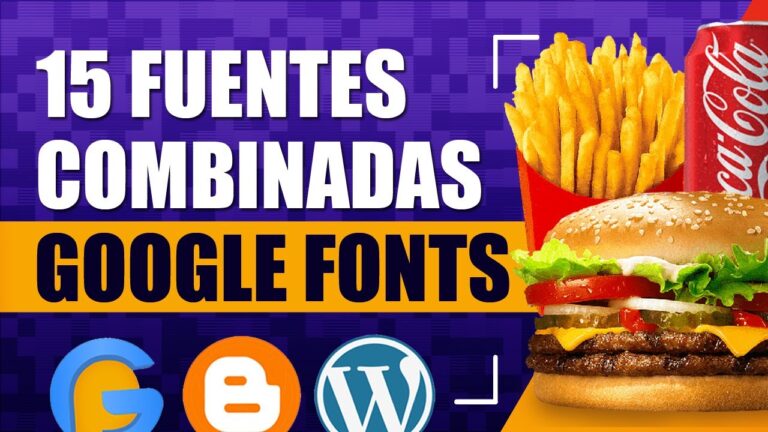
La combinación de tipografías en el diseño web es un arte que puede transformar la estética y la funcionalidad de una página. Elegir las fuentes adecuadas no solo mejora la legibilidad, sino que también refuerza la identidad de marca y crea una experiencia visual atractiva para los usuarios. En un mundo digital donde la primera impresión cuenta, dominar esta técnica se vuelve esencial para cualquier diseñador que busque destacar en un mar de contenido. Exploramos las mejores prácticas y estrategias para lograr una armonía tipográfica que cautive y comunique eficazmente.
¿Cuántas tipografías se sugiere usar en un diseño web?
Al diseñar una página web, se recomienda utilizar entre dos y tres tipografías para mantener una estética limpia y coherente. Una combinación rendidora puede ser la fusión de tipografías sans serif y serif, que aporta un contraste atractivo y mejora la legibilidad. Este enfoque no solo evita que el diseño se sienta abrumador, sino que también realza la experiencia del usuario, facilitando la navegación y la comprensión del contenido.
¿Cuántas fuentes son apropiadas para utilizar en un sitio web?
Al diseñar un sitio web, la elección de tipografías es fundamental para lograr una comunicación rendidora y estética. Aunque no existe una regla estricta sobre cuántas tipografías se deben emplear, lo ideal es limitarse a un máximo de tres. Esta restricción no solo ayuda a mantener una apariencia coherente, sino que también facilita la lectura y la navegación del usuario.
Optar por una tipografía versátil puede ser una excelente estrategia. Al encontrar una fuente que se adapte bien a la identidad del sitio, es posible utilizar diferentes pesos, como regular, medium y bold, para resaltar información importante sin necesidad de introducir nuevas tipografías. De este modo, se logra un equilibrio visual que mantiene la atención del visitante y refuerza la jerarquía del contenido.
Además, al limitar el número de tipografías, se mejora la carga del sitio y se optimiza la experiencia del usuario. Un diseño limpio y ordenado no solo es más atractivo, sino que también ayuda a transmitir el mensaje de manera clara y directa. En resumen, la clave está en la selección cuidadosa de tipografías que se complementen entre sí, creando una armonía que beneficie tanto la estética como la funcionalidad del sitio web.
¿Cómo puedo combinar fuentes?
Combinar fuentes de manera rendidora es un arte que puede realzar visiblemente cualquier diseño. Para lograr una armonía visual, es clave elegir tipografías que se complementen entre sí. Una buena práctica es seleccionar una fuente para los encabezados que sea audaz y llamativa, y una más sencilla y legible para el cuerpo del texto. Esto no solo crea un atractivo visual, sino que también mejora la legibilidad y la jerarquía de la información.
Además, es recomendable limitar la combinación a dos o tres tipos de fuentes para evitar una apariencia desordenada. Las fuentes serif, por ejemplo, pueden funcionar bien con sans-serif, creando un contraste interesante. También puedes jugar con diferentes pesos y estilos de una misma familia tipográfica, lo que permite mantener la cohesión mientras se añade variedad al diseño.
Por último, considera el contexto y la audiencia al seleccionar tus fuentes. Cada tipografía evoca diferentes emociones y asociaciones, por lo que es fundamental que elijas aquellas que reflejen la personalidad de tu mensaje. Al seguir estas pautas, podrás crear combinaciones de fuentes impactantes que no solo sean estéticamente agradables, sino también funcionales.
Potencia Tu Diseño con la Tipografía Adecuada
La tipografía es un elemento fundamental en el diseño gráfico que puede transformar por completo la percepción de un mensaje. Elegir la fuente adecuada no solo mejora la legibilidad, sino que también puede evocar emociones y establecer una conexión más profunda con el público. Al considerar el estilo, el tamaño y el interlineado, los diseñadores pueden crear una jerarquía visual que guíe al espectador a través del contenido de manera rendidora.
Además, la tipografía actúa como un reflejo de la identidad de una marca. Fuentes modernas y limpias pueden transmitir innovación y frescura, mientras que tipos de letra más clásicos pueden evocar tradición y confianza. Al alinear la elección tipográfica con los valores y la personalidad de la marca, se refuerza el mensaje y se crea una experiencia coherente para el usuario.
Finalmente, no subestimes el poder de la combinación de tipografías. Un diseño bien equilibrado puede utilizar diferentes fuentes para destacar información clave y crear un contraste atractivo. Experimentar con tipografías complementarias permite no solo enriquecer el diseño, sino también atraer la atención y mantener el interés del espectador. Potenciar tu diseño con la tipografía adecuada es una estrategia clave para lograr un impacto duradero.
El Arte de Mezclar Fuentes para Impacto Visual
La combinación de tipografías en el diseño web es un arte que puede transformar la experiencia del usuario y potenciar la identidad visual de una marca. Al elegir cuidadosamente las fuentes y mantener un equilibrio entre legibilidad y estética, los diseñadores pueden crear interfaces atractivas y funcionales. Dominar esta habilidad no solo mejora la comunicación visual, sino que también invita a los usuarios a explorar y disfrutar del contenido, convirtiendo la tipografía en un elemento clave del diseño digital.